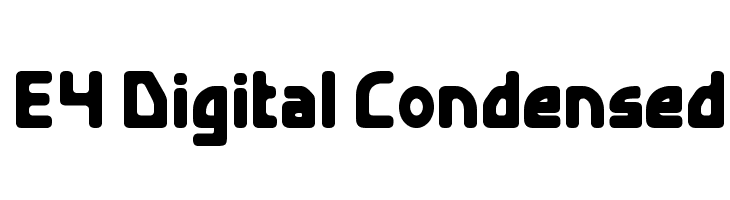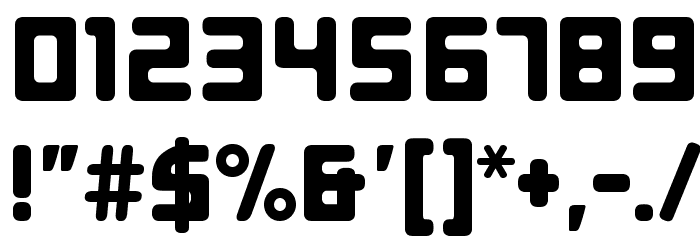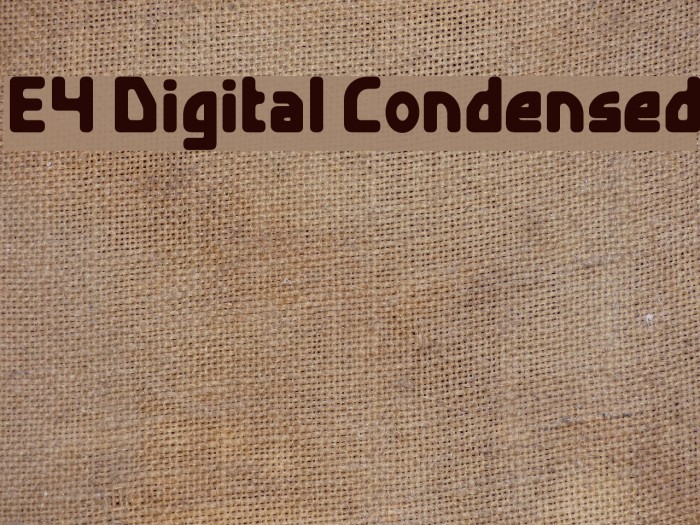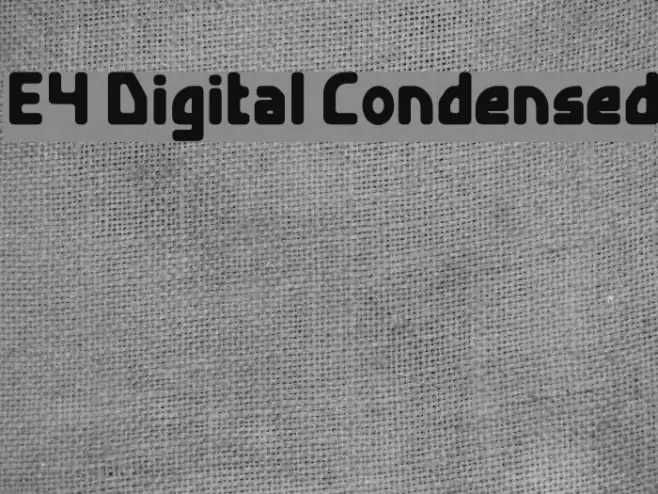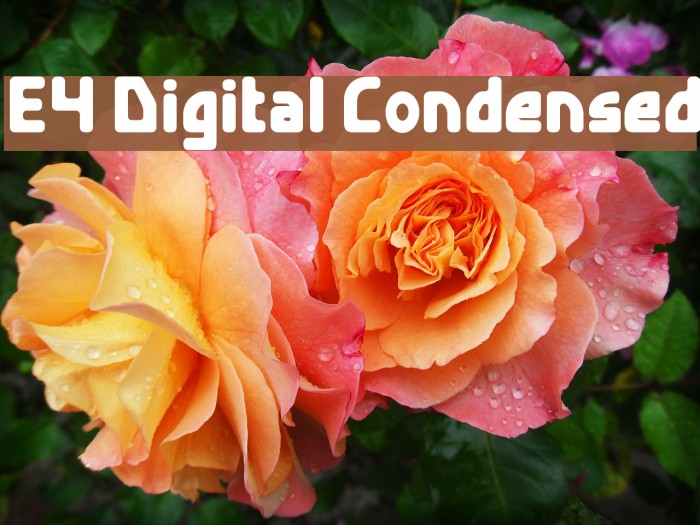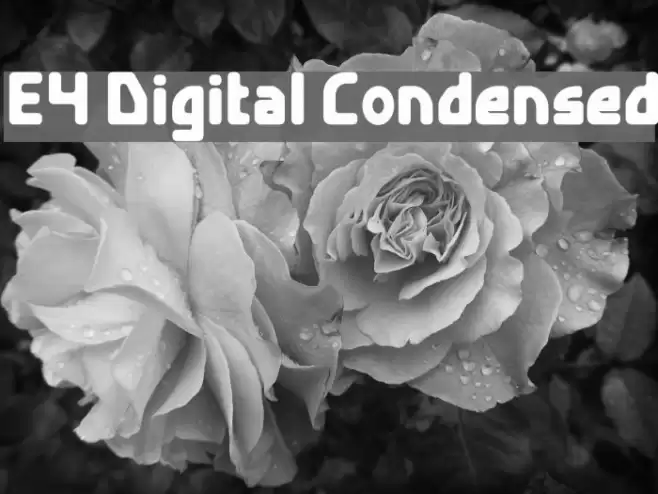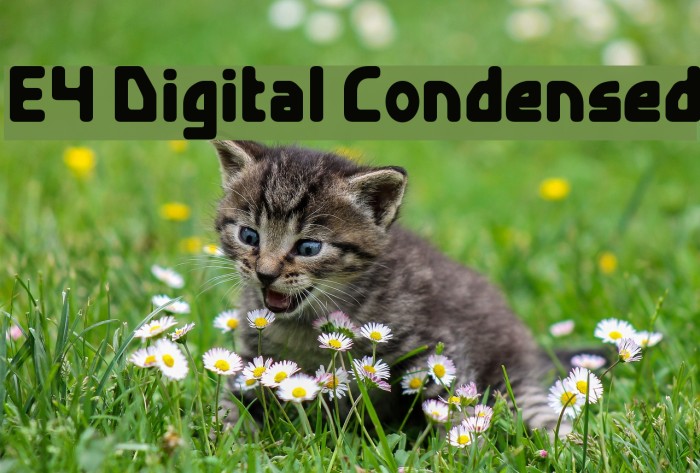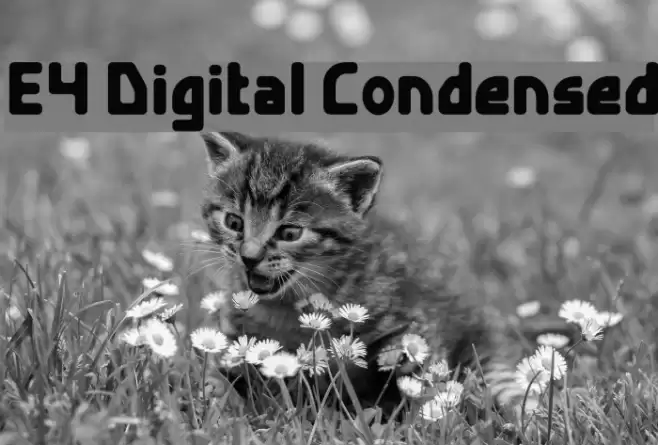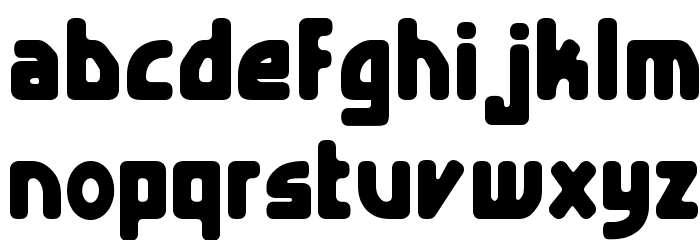
E4 Digital Condensed Font
| 用途 | Headlines, Logos, Digital Interfaces |
| おすすめプロジェクト | Ideal for tech-related branding, digital interfaces, modern posters, and futuristic design projects. |